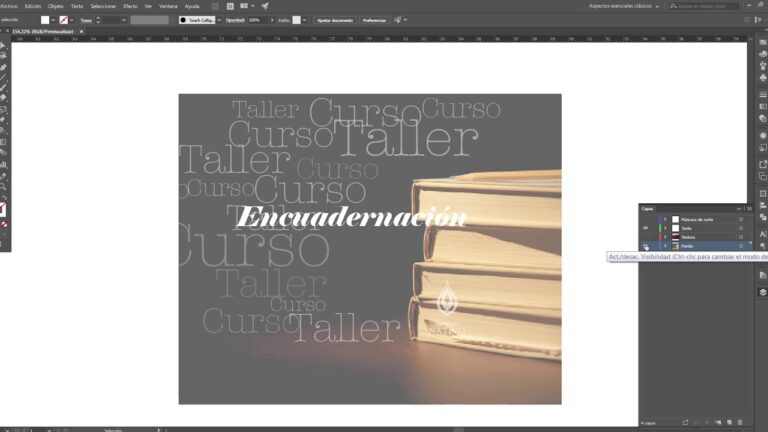
Explorando Fuentes Tipográficas Innovadoras en el Diseño Gráfico
El diseño gráfico está en constante evolución, y una de las tendencias más emocionantes en la actualidad es la exploración de nuevas fuentes tipográficas. Al experimentar con tipografías innovadoras, los diseñadores no solo enriquecen su trabajo, sino que también logran transmitir mensajes de manera más efectiva y creativa. Este artículo se adentra en el fascinante mundo de las tipografías emergentes, analizando su impacto en la estética visual y la comunicación en el diseño gráfico contemporáneo.
¿Cuál es la relevancia de la tipografía en el diseño gráfico?
La tipografía es fundamental en el diseño gráfico, ya que no solo se trata de elegir fuentes adecuadas, sino de cómo estas influyen en la comunicación y la percepción de un mensaje. Su correcta aplicación puede reforzar la identidad de una marca, haciendo que esta sea memorable y reconocible. Además, una tipografía bien elegida mejora la usabilidad y enriquece la experiencia del usuario, asegurando que el contenido sea no solo atractivo, sino también accesible y fácil de leer.
¿Qué son las fuentes tipográficas y cuáles son sus clasificaciones?
Las fuentes tipográficas son estilos visuales que agrupan caracteres, como letras y signos, con características gráficas compartidas, diseñadas para transmitir mensajes de manera efectiva. Se clasifican en diversas categorías según sus rasgos, como las serifas, que tienen pequeñas extensiones al final de las letras, y las sans serifas, que son más limpias y modernas. Otras clasificaciones incluyen las fuentes script, que imitan la escritura manual, y las display, diseñadas para llamar la atención en títulos y carteles. Cada tipo de fuente aporta una personalidad única al texto, influenciando la percepción del mensaje.
¿Qué se entiende por tipografía en el diseño?
La tipografía, derivada del griego que significa molde de escritura, es un elemento fundamental en el diseño gráfico. Se define como el arte de organizar letras de manera que el texto no solo sea legible, sino que también se integre estéticamente en la composición del material. Al elegir la tipografía adecuada, los diseñadores pueden transmitir emociones y mensajes específicos, elevando así la efectividad del contenido visual y mejorando la experiencia del espectador.
Redefiniendo la Estética Visual con Tipografía Moderna
La tipografía moderna ha revolucionado la forma en que percibimos y experimentamos el diseño visual. Con líneas limpias, formas geométricas y una paleta de colores vibrantes, esta estética no solo mejora la legibilidad, sino que también transmite una sensación de frescura y contemporaneidad. Al incorporar tipografías audaces y únicas, los diseñadores pueden crear composiciones que capturan la atención del espectador, generando un impacto inmediato y duradero.
A medida que avanzamos en la era digital, la tipografía se convierte en un elemento clave para contar historias visuales efectivas. La versatilidad de las fuentes modernas permite que marcas y proyectos se destaquen en un mar de información, facilitando la conexión emocional con su audiencia. Al redefinir la estética visual a través de la tipografía, no solo se embellece el contenido, sino que también se potencia la comunicación, haciendo que cada palabra cuente de manera significativa.
La Revolución Tipográfica: Creatividad sin Límites
La Revolución Tipográfica transformó el paisaje de la comunicación visual, liberando a las ideas de las ataduras de la escritura manual. Con la invención de la imprenta por Johannes Gutenberg en el siglo XV, el acceso a la lectura y la difusión del conocimiento se expandieron exponencialmente. Este avance tecnológico no solo facilitó la producción masiva de libros, sino que también democratizó la educación, permitiendo que un número cada vez mayor de personas pudiera acceder a la información.
A medida que las técnicas tipográficas evolucionaron, la creatividad floreció en formas inesperadas. Diseñadores y tipógrafos comenzaron a experimentar con estilos, fuentes y composiciones, llevando la estética a nuevos niveles. La tipografía se convirtió en un medio poderoso para expresar emociones y conceptos, influenciando el arte, la publicidad y la cultura popular. Cada letra, cada palabra, se transformó en un vehículo de expresión que podía captar la atención y provocar una respuesta inmediata.
Hoy en día, la Revolución Tipográfica sigue resonando en el mundo digital, donde la tipografía no solo es un elemento funcional, sino también una herramienta esencial para la narrativa visual. La variedad de fuentes y estilos disponibles permite a los creadores de contenido explorar su creatividad sin límites, dando vida a sus ideas de maneras innovadoras y cautivadoras. En este contexto, la tipografía se reafirma como un arte en constante evolución, capaz de conectar y comunicar en un mundo cada vez más interconectado.